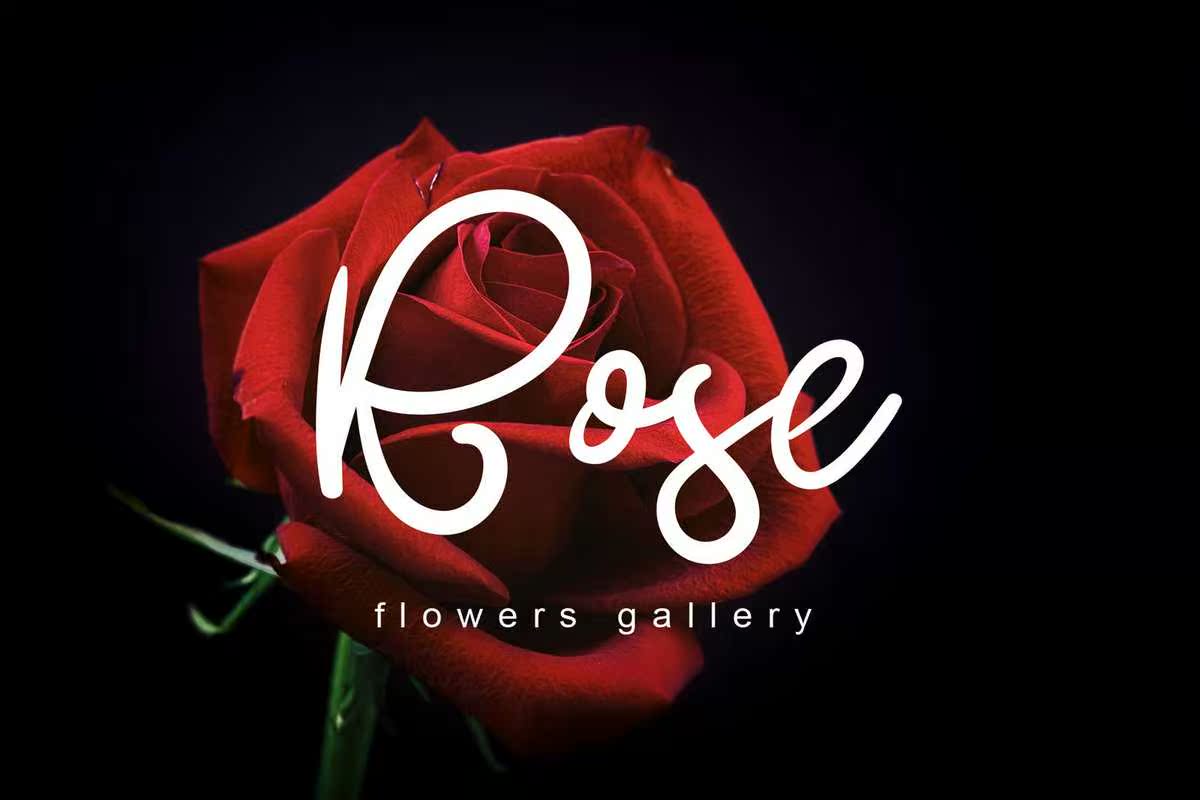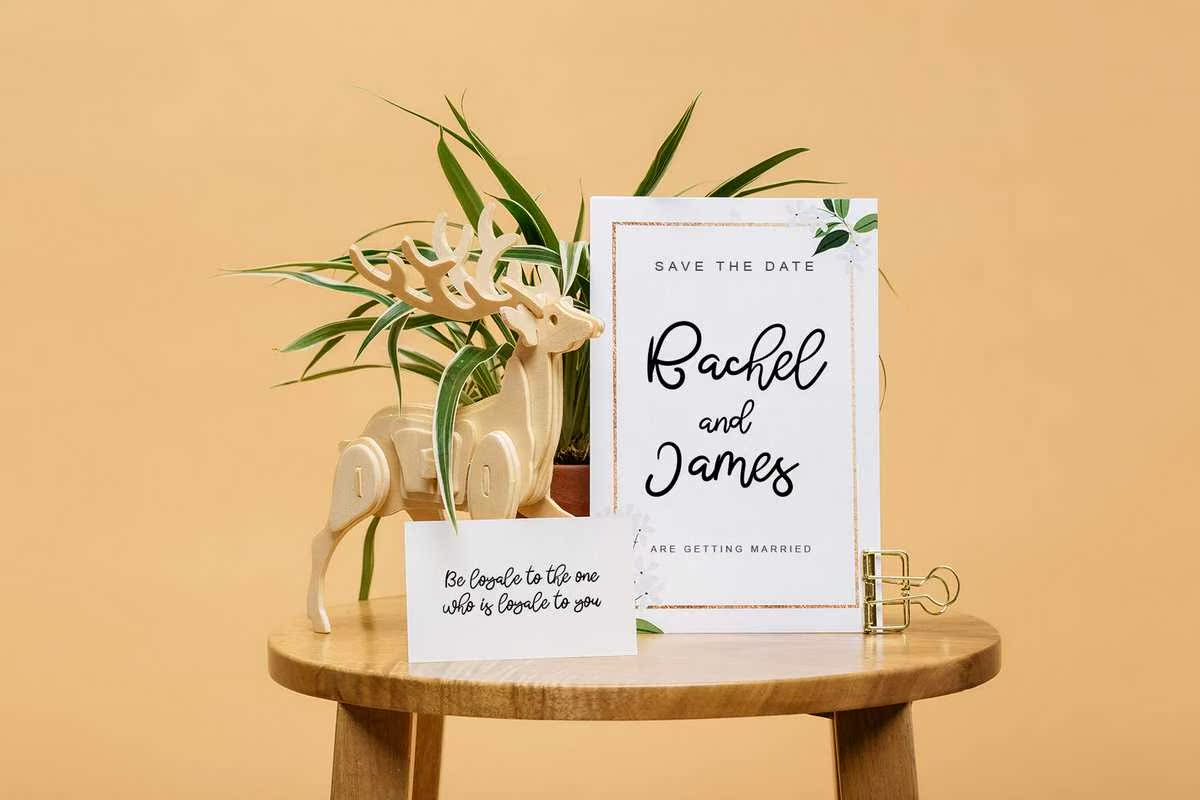
Butterfly–AlovelyScriptFonts是一款手工书写的字体,风格独特,非常适合您的下一个创意项目,包括用于信封、徽标、排版、品牌和问候卡、打印报价、邀请函、卡片、产品包装、标题、徽标、信头、海报、服装设计、标签、,等等。Butterfly–AlovelyScriptFont是一款手工书写的字体,风格独特,非常适合您的下一个创意项目,包括用于凸版、徽标、排版、品牌和问候卡、打印报价、邀请函、卡片、产品包装、页眉、徽标、信头、海报、服装设计、标签等的弹出式标签集。。